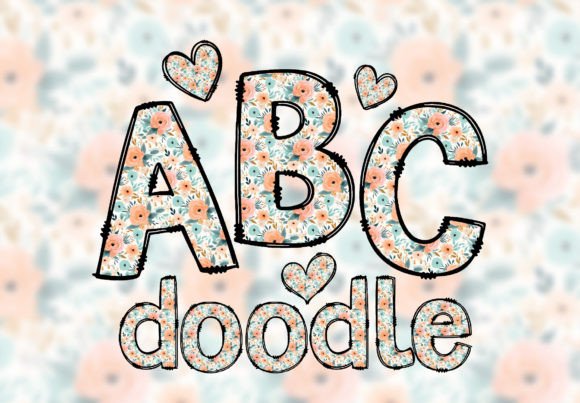
Cute Floral Alphabet Doodle Letters Font
Якщо ви шукаєте високоякісні ресурси, такі як Cute Floral Alphabet Doodle Letters Font, цей преміум-пакет є фантастичним вибором для ваших творчих проектів.
Створений з високою точністю, Cute Floral Alphabet Doodle Letters Font забезпечує чисті вектори, плавну типографіку та комерційну ліцензію для вашого спокою.